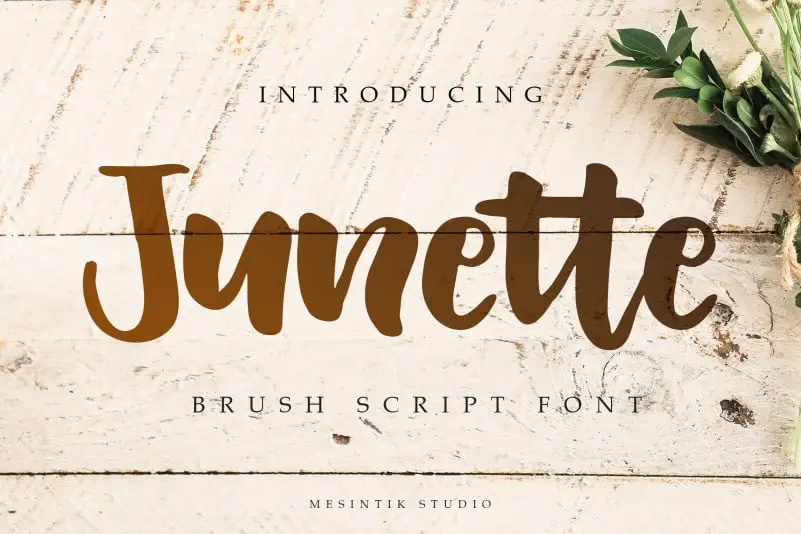
Junette Script Font – Download Grátis
A Junette Script Font é uma elegante tipografia script feita sob a forma de traço de pincel, com um estilo de escrevermanual que destaca sua naturalidade e elegância. Ideal para diversos projetos, essa fonte é perfeita tanto para trabalhos profissionais quanto para ambientes mais relaxantes ou criativos. Mesinitik Studio apresenta esta fonte como uma adição fascinante ao seu catálogo de Brush Fonts, oferecendo uma maneira única e sofisticada para personalizar textos e gráficos. Com Junette Script Font, você pode criar um texto atraente que vai se destacar em qualquer projeto. Suas linhas fluidas e detalhes sutis refletem o estilo elegante de escrita-mão, garantindo uma aparência natural e profissional ao mesmo tempo. Seja para adicionar um toque pessoal a um documento corporativo ou para criar um design exclusivo que chama a atenção na web, essa fonte é uma escolha ótima. Mesinitik Studio apresenta Junette Script como uma opção versátil que combina estilo e praticidade em um único gráfico de texto.